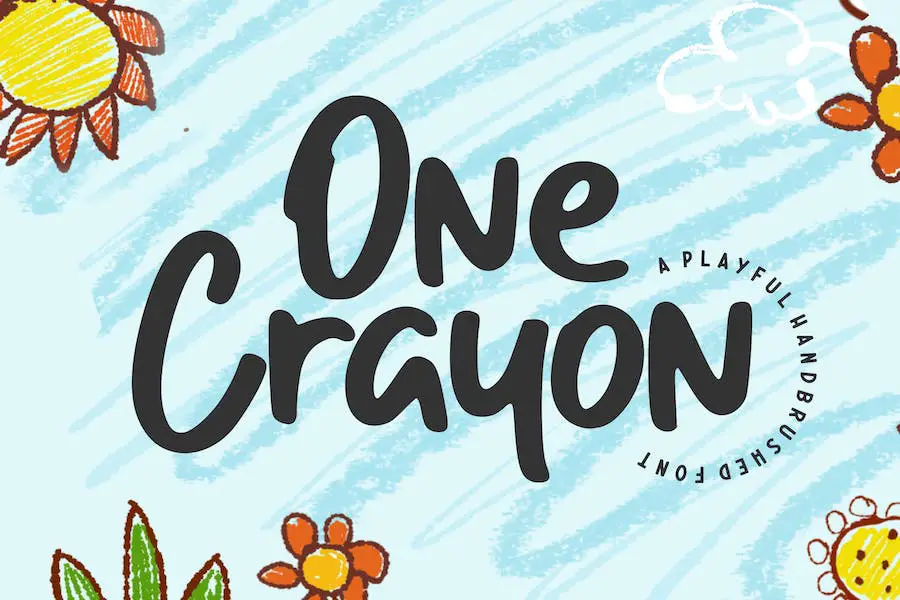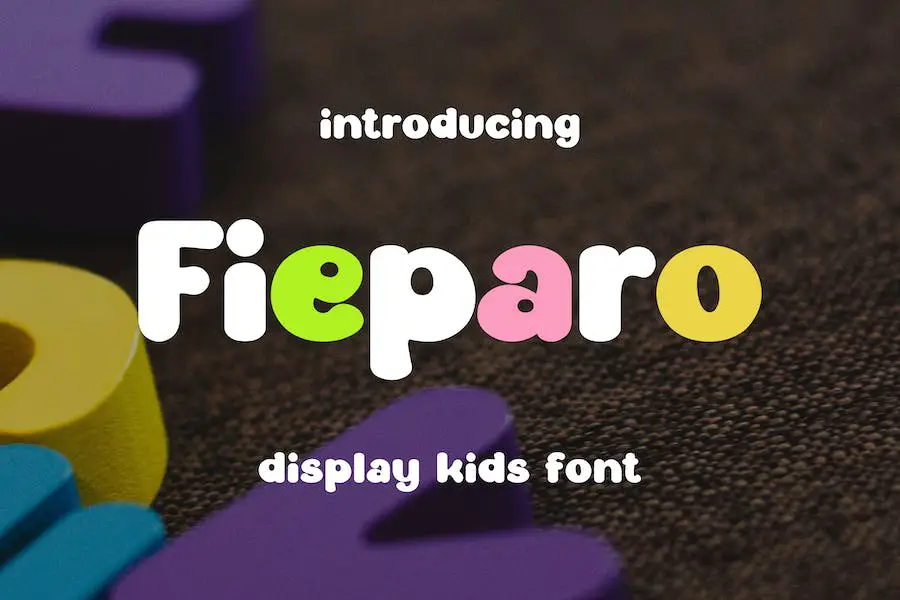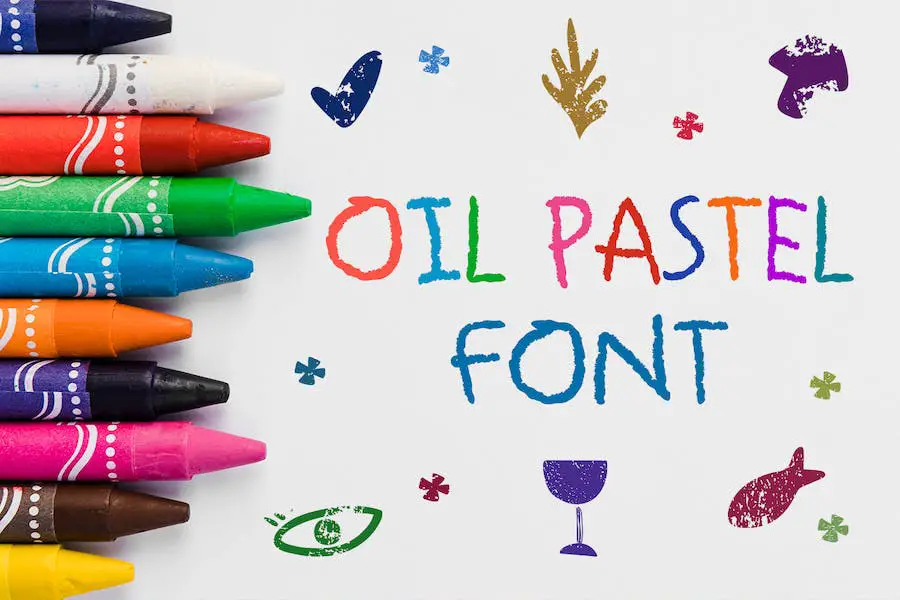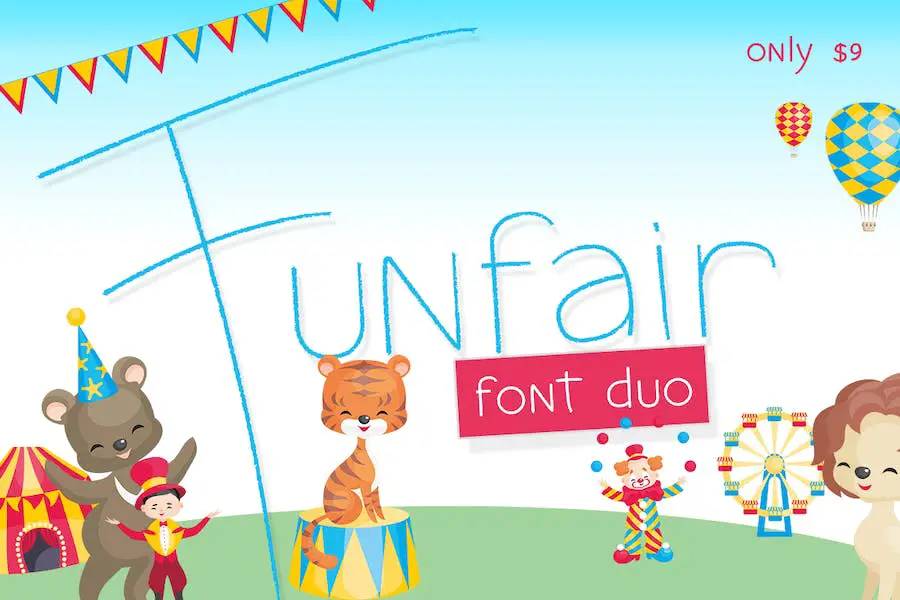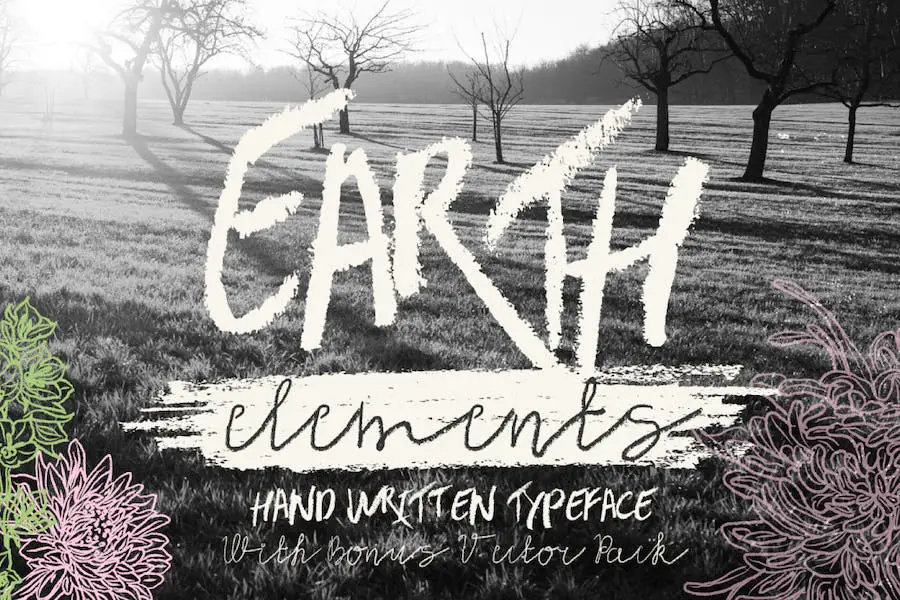
24 أفضل خطوط تلوين لعام 2023 (مجانية ومميزة)
نشرت: 2023-09-23هل تساءلت يومًا كيف يمكنك الارتقاء بمشاريع التصميم الجرافيكي الخاصة بك إلى المستوى التالي؟ هل تبحث عن خط يمكنه تحسين التصميم على الفور وجعله أكثر جاذبية من الناحية المرئية؟ لا مزيد من البحث، لأنه في منشور المدونة هذا، سنستكشف عالم Crayon Fonts!
تعد Crayon Fonts طريقة فريدة ومبتكرة لإضافة لمسة إضافية إلى تصميماتك. بفضل مظهرها المرح والنابض بالحياة، يمكنها إضفاء شعور بالمرح والحنين إلى أي مشروع.
سواء كنت تصمم غلاف كتاب للأطفال، أو دعوة عيد ميلاد، أو شعارًا لمتجر ألعاب، يمكن لـ Crayon Fonts إضافة العنصر المثالي لجعل تصميمك مميزًا.
هل تعلم أن Crayon Fonts أصبحت ذات شعبية متزايدة بين مصممي الجرافيك في السنوات الأخيرة؟
في الواقع، وفقًا لاستطلاع أجرته إحدى مجلات التصميم الرائدة، يعتقد 68% من المصممين أن استخدام Crayon Fonts في مشاريعهم قد أدى إلى تحسين المظهر البصري العام بشكل ملحوظ.
وهذا ليس مفاجئًا بالنظر إلى أن Crayon Fonts تضيف لمسة من الإبداع وتثير إحساسًا بالمرح الذي يتردد صداه لدى كل من الأطفال والكبار على حدٍ سواء.
في هذه المقالة، سوف نتعمق أكثر في عالم خطوط Crayon ونستكشف الأنماط والأشكال المختلفة المتوفرة.
سنزودك أيضًا ببعض النصائح والحيل حول كيفية دمج خطوط Crayon بفعالية في تصميماتك. لذا، احصل على أقلام التلوين الافتراضية الخاصة بك واستعد لإطلاق العنان لطفلك الذي بداخلك بينما نبدأ هذه الرحلة الإبداعية معًا!
أفضل خطوط تلوين متميزة
هل تبحث عن إضافة لمسة من الإبداع والمرح لمشاريع التصميم الخاصة بك؟ من المؤكد أن مجموعتنا من أفضل خطوط أقلام التلوين المتميزة ستجلب هذا السحر والشخصية الإضافية إلى الطباعة الخاصة بك.
استعد لاستكشاف عالم من الحروف النابضة بالحياة والمرسومة يدويًا والتي ستجعل تصميماتك بارزة حقًا! لا تفوت فرصة استخدام هذه الخطوط الرائعة التي ستأخذ مشروعاتك إلى مستوى جديد تمامًا من الإبداع.
تلوين الملك
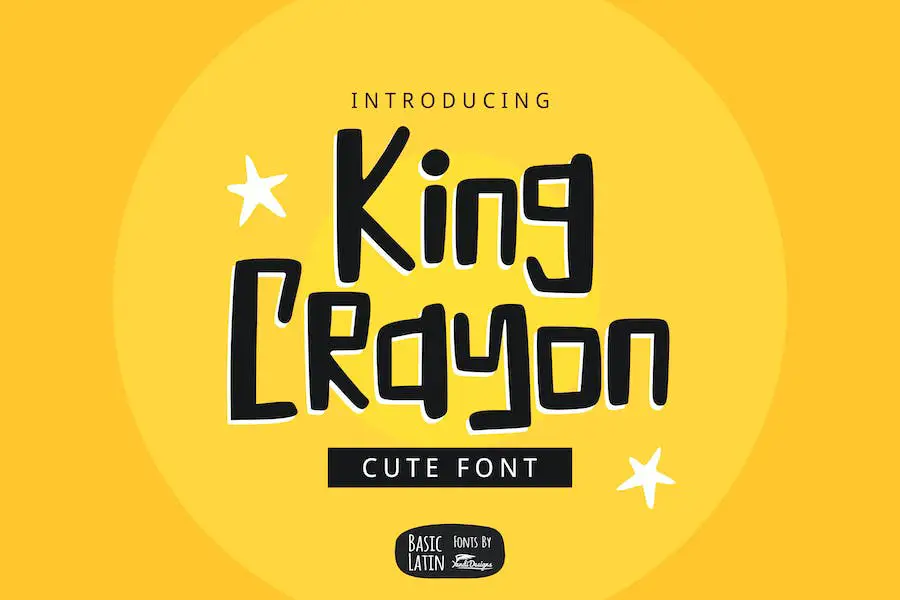
King Crayon هو خط مبهج يضفي لمسة من النزوة والإبداع على أي مشروع تصميم رسومي.
يعد هذا الخط البسيط والساحر المصنوع يدويًا مثاليًا لكتب الأطفال والاقتباسات والشعارات والعناوين والمزيد. بفضل طبيعته متعددة الأغراض، فإنه يوفر إمكانيات لا حصر لها للمصممين الذين يتطلعون إلى إضافة عنصر فريد وممتع إلى عملهم.
سواء كنت تعمل على كتاب للأطفال، أو شعار، أو تصميم اقتباس، أو أي مشروع إبداعي آخر، فإن King Crayon يلبي احتياجاتك. إن بساطته وجاذبيته تجعله خيارًا مفضلاً للمصممين الذين يرغبون في إضفاء إحساس بالمرح والإبداع على عملهم.
رسائل تلوين
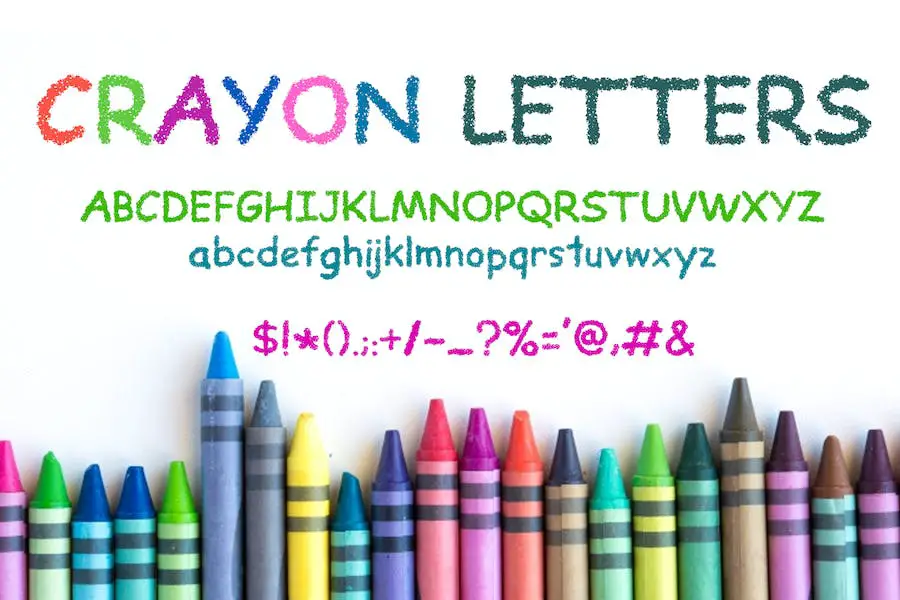
Crayon Letters هو خط مذهل وفريد من نوعه مكتوب بخط اليد يضفي لمسة من السحر والحيوية على أي تصميم. بفضل أسلوبه البسيط والملون، يعد هذا الخط مثاليًا لإضافة عنصر مرح ومبدع إلى مشاريعك.
يكمن جمال Crayon Letters في جماليتها المرسومة يدويًا، والتي تضفي على تصميماتك لمسة شخصية وفريدة من نوعها. سواء كنت تعمل على شعار أو ملصق أو رسم على وسائل التواصل الاجتماعي، فإن خط Adobe Crayon هذا يضيف طابعًا وإبداعًا على الفور.
بالإضافة إلى جاذبيته البصرية وتعدد استخداماته، فإن Crayon Letters سهل الاستخدام بشكل لا يصدق. تضمن أشكال الحروف الواضحة والمقروءة بقاء النص الخاص بك قابلاً للقراءة، بينما توفر اللمسات الملونة لمسة إضافية من الاهتمام البصري.
سواء كنت مصممًا متمرسًا أو بدأت للتو، ستجد أن Crayon Letters بديهي وسهل الاستخدام.
تلوين الطفل
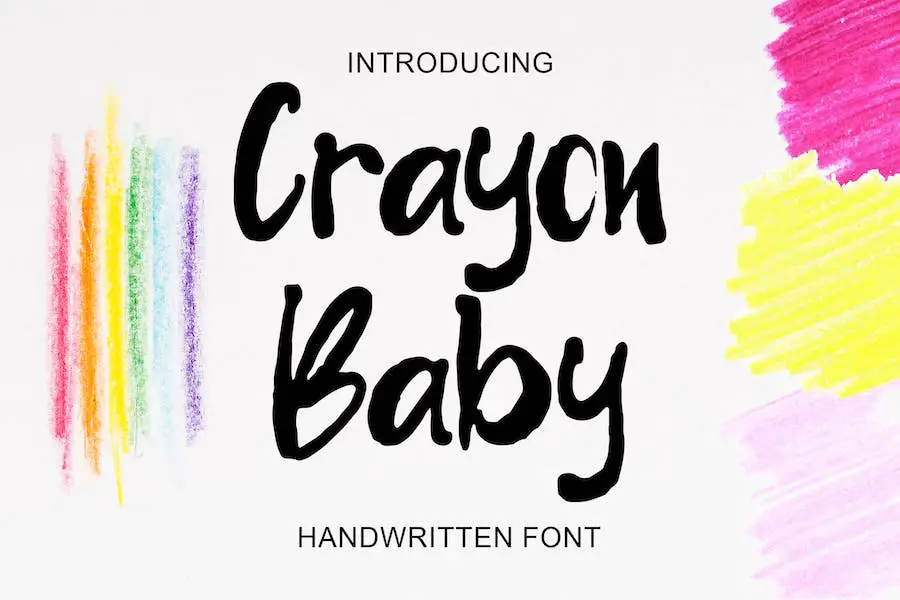
Crayon Baby هو خط متعدد الاستخدامات يعمل على كل من أجهزة Mac والكمبيوتر الشخصي. إنه خط مكتوب بخط اليد يضيف لمسة طبيعية لتصميماتك، مما يجعل كل التفاصيل جميلة.
سواء كنت تعمل على دعوة أو غلاف كتاب أو أي مشروع تصميم آخر، فإن هذا الخط مثالي. يتضمن خط Crayon الخاص بـ Word أرقامًا وعلامات ترقيم وأحرفًا صغيرة وكبيرة.
بالإضافة إلى ذلك، فهو يدعم الأحرف متعددة اللغات مثل a، o، u، Ä، O، U، ß، و. وهو أيضًا مشفر بـ PUA، مما يعني أنه يمكنك الوصول إلى جميع الحروف الرسومية. مع Crayon Baby، ستتمتع تصميماتك بهذا الشعور الأصيل المصنوع يدويًا والذي سيثير إعجابك حقًا.
علامة الطباشير
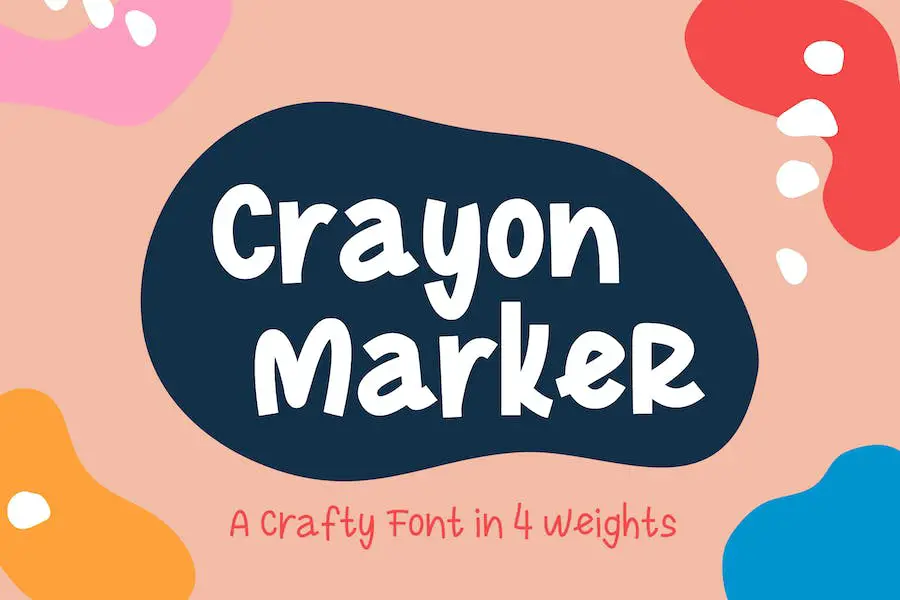
يعد خط Crayon Marker محرفًا غريبًا ومبتكرًا يضيف لمسة مرحة إلى أي مشروع.
مع أربعة أوزان مختلفة للاختيار من بينها، لديك حرية المزج والمطابقة للحصول على المظهر والملمس المثالي.
يعد هذا الخط متعدد الاستخدامات مثاليًا للشعارات والاقتباسات والدعوات وبطاقات المعايدة والمجلات وفن جدار غرفة الأطفال وملابس الأطفال وغير ذلك الكثير.
باستخدام خط Crayon Marker، يمكنك على الفور إضفاء إحساس بالمرح والمرح على تصميماتك. سواء كنت تصمم شعارًا لطيفًا لعلامة تجارية خاصة بالأطفال أو تضيف لمسة غريبة إلى بطاقة تهنئة، فإن خطوط Crayon هذه لـ Canva ستضفي الحيوية على أفكارك.
فلماذا الانتظار؟ أطلق العنان لخيالك مع خط Crayon Marker وانتقل بتصميماتك إلى المستوى التالي من الإبداع والسحر. أطلق العنان لطفلك الداخلي وابدأ في التصميم باستخدام هذا الخط المبهج اليوم!
قلم تلوين
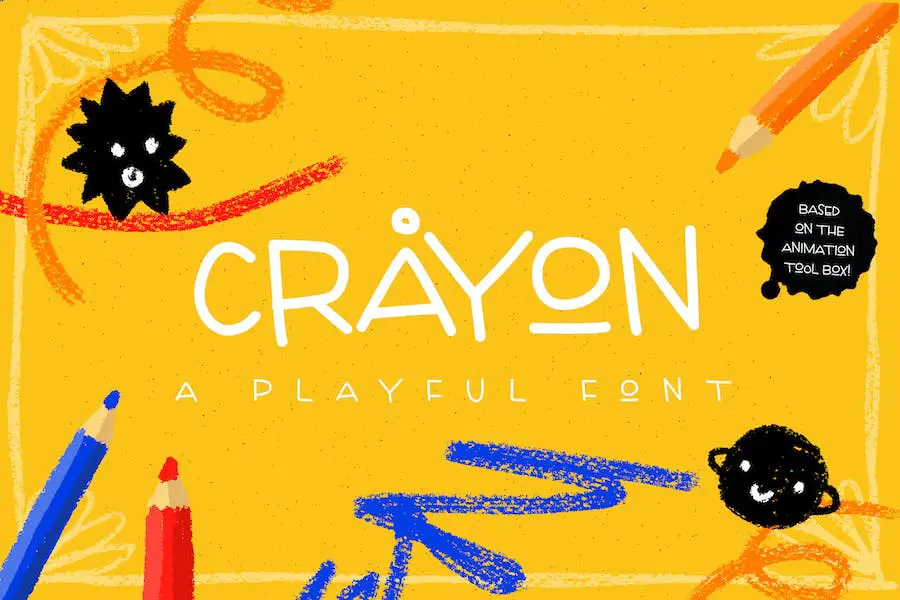
Crayon هو خط كبير مبهج يضيف لمسة مرحة إلى مشاريع التصميم الخاصة بك. مثالي لإنشاء أعمال فنية هزلية، أو دعوات للأطفال، أو حفلات الأطفال، هذا الخط المصنوع يدويًا يضفي لمسة جمالية ممتعة ومستديرة على تصميماتك.